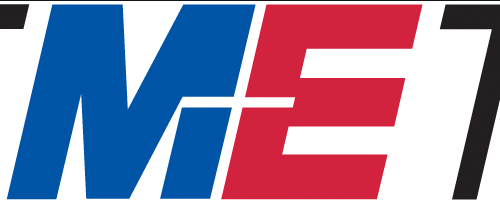
Hm, ist das zweiteilig, gekoppelt durch ein "+", Teil 1 hört mit M auf und Teil 2 fängt mit F an?
auf den ersten blick sahs aus wie das alte amway logo.
fluglinie?
Nein.
Hm, ist das zweiteilig, gekoppelt durch ein "+", Teil 1 hört mit M auf und Teil 2 fängt mit F an?
Bis auf das F ist das völlig richtig analysiert.
Ich würde MH vermuten und bin eher auf dem Spielzeugtrip...
Ist das Nicht-F ein P wie Partner?
Nein.
Kursiv, grotesk, klare Farben:
Ja.
Elekronik-Handelsmarke oder was aus der Drogerie?
Nein.
Ist das Nicht-F ein P wie Partner?
Nein.
Ich würde MH vermuten und bin eher auf dem Spielzeugtrip...
Weder H noch Spielzeug.
Tipp: Das Logo erscheint etwa einmal im Jahr prominent in der Tagesschau.
Nein, nichts christliches. Ich hielt den Laden für recht bekannt, doch langsam kommen mir Zweifel. Tipp: Ihr werdet das Logo immer dann sehen, wenn über bestimmte Tarifverhandlungen berichtet wird.